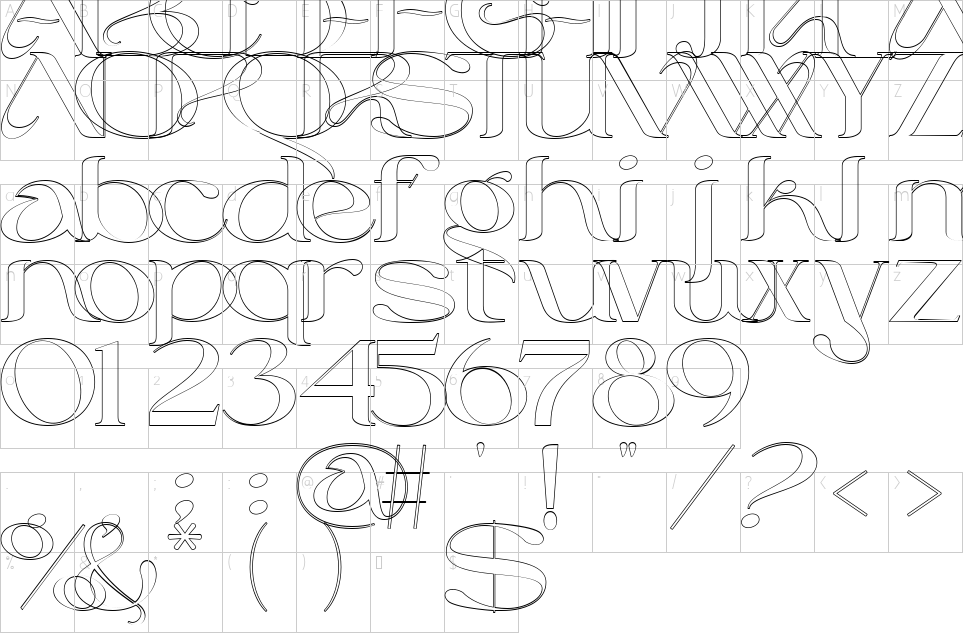
A fonte Maroon And Black é uma opção de fonte elegante e envolvente, perfeita para ambientes gráficos modernos. Desenvolvida pela equipe da Areatype, essa fonte traz o conceito de marrom escuro e preto em sua simplicidade e elegância, que vai muito além de um simples efeito de aparência. Com seu design minimalista, a Maroon And Black combina perfeitamente com diversos estilos de design, desde tipografias minimalistas até gráficos de alta qualidade. Esta fonte é uma ótima escolha para criações que buscam um equilíbrio entre sofisticação e simplicidade, fazendo-a uma excelente opção para designers gráficos e web designers que buscam um recurso para seu trabalho. Descarregada 1.596 vezes, a Maroon And Black é uma fonte de alta qualidade que vale a pena explorar.